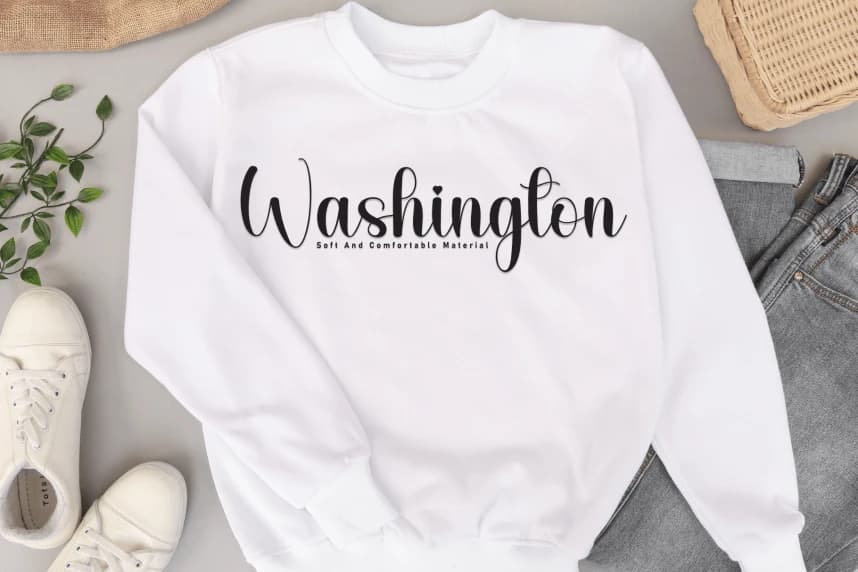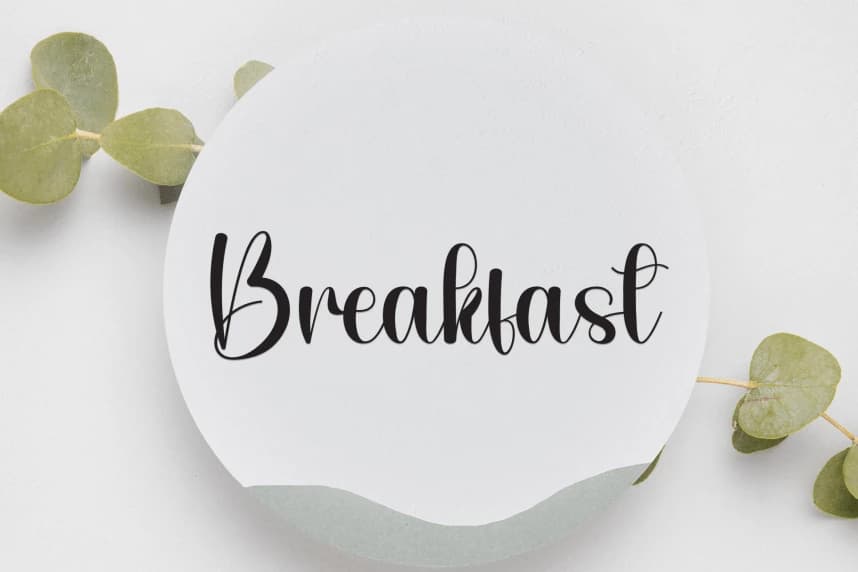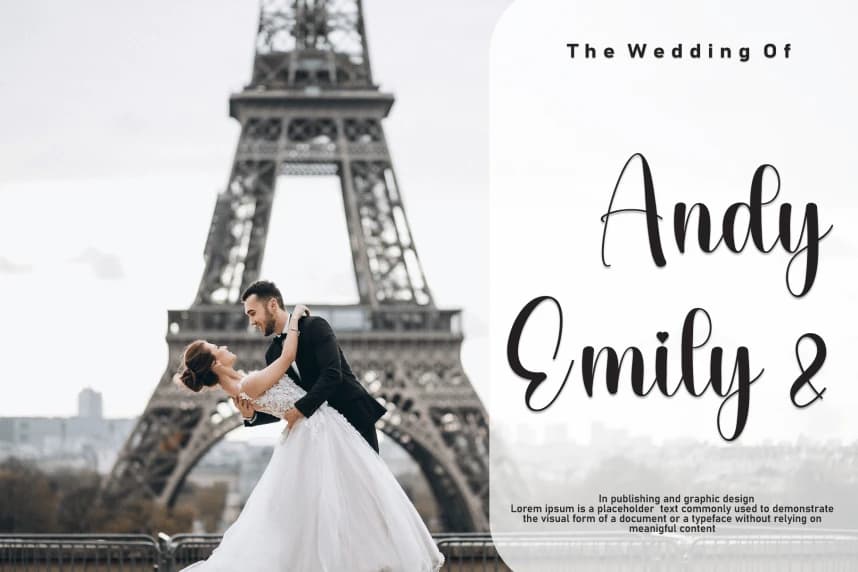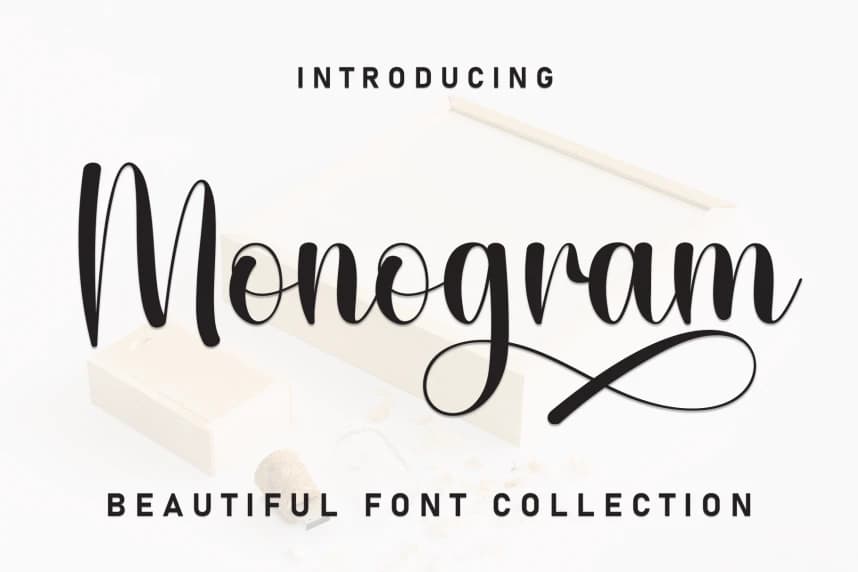
Monogram – New Style Handwritten Font, tatlı ve dostça bir el yazısı gösterim fontudur. Şirin ve eğlenceli olan bu font, düğün davetiyelerini, kartları yazmak için ya da oyuncu bir dokunuşa ihtiyaç duyabilecek her türlü tasarım için idealdir!
Monogram – New Style Handwritten Font, tatlı ve dostane bir el yazısı gösterim fontudur. Şirin ve eğlenceli olan bu font, düğün davetiyelerini yazmak, kartlar veya eğlenceli bir dokunuşa ihtiyaç duyabilecek diğer herhangi bir tasarım için idealdir!